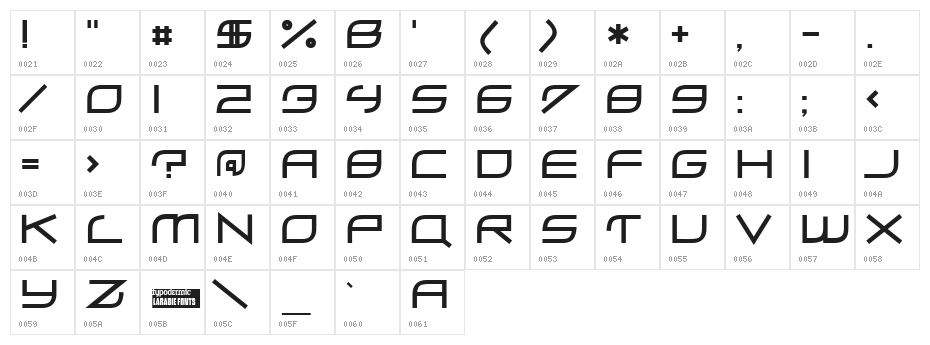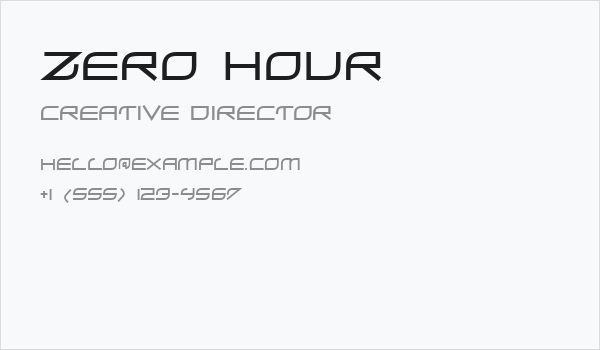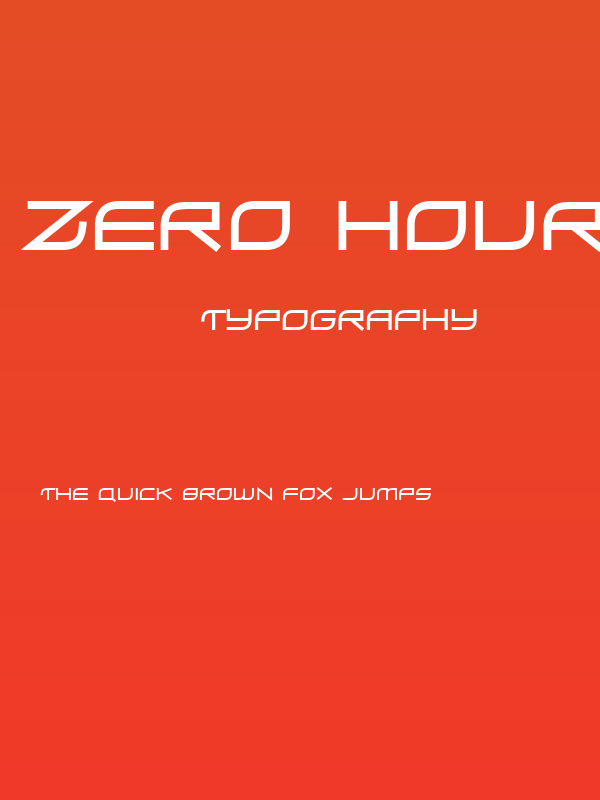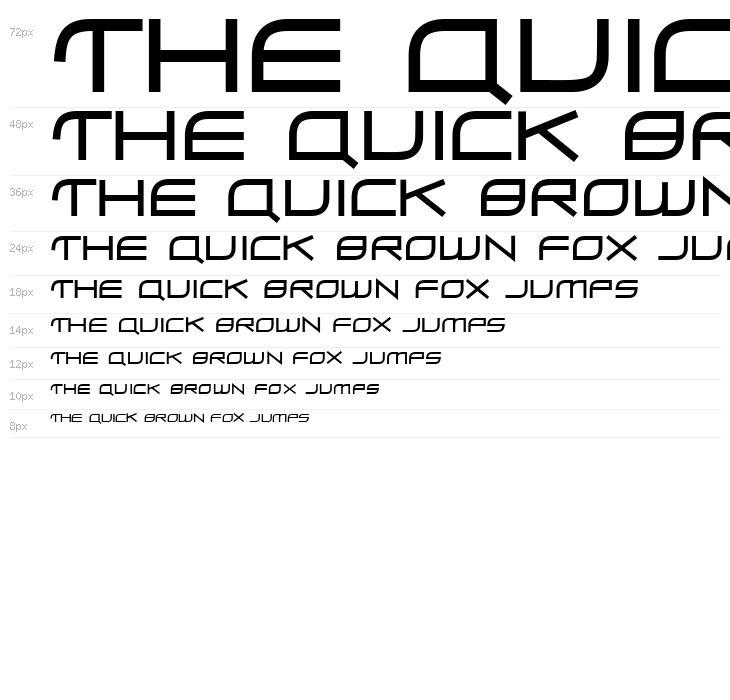
Zero Hour Font
| Категория | Sci-fi |
| Область применения | Headlines, Logos, Digital Interfaces |
| Рекомендуемые проекты | Ideal for technology branding, sci-fi themed designs, modern advertising, and digital interfaces. |